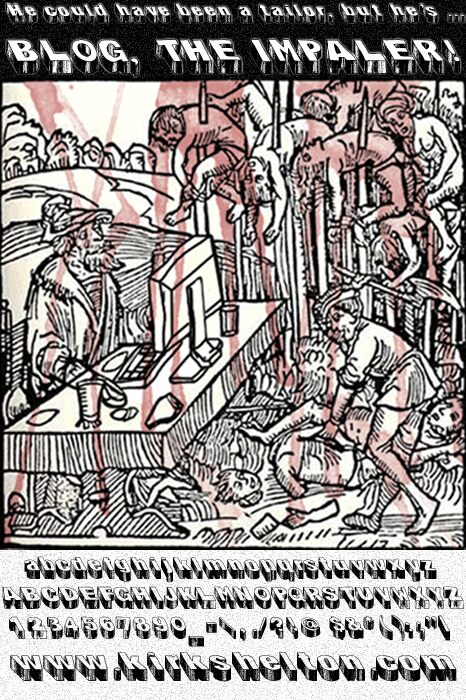
Blog the Impaler Caps Heavy autorstwa Kirka Sheltona to darmowy font 3D składający się z wielkich liter, wyróżniający się masywnymi formami i wyraźnie zarysowaną głębią. Szerokie płaszczyzny czołowe osadzone są na głębokich, kątowych bokach, a szorstkie plamki i zadrapania nadają blokowym kształtom surowy, industrialny charakter.
Ten darmowy krój świetnie sprawdzi się na plakatach koncertowych, w brandingu salonów gier, na okładkach płyt z horrorami komediowymi, ulotkach wydarzeń oraz w tytułach komiksów. Najlepiej prezentuje się w krótkich formach, takich jak plansze tytułowe czy hasła reklamowe, gdzie przesadna ekstruzja może w pełni wybrzmieć, a tekstura powierzchni pozostaje wyraźnie widoczna.